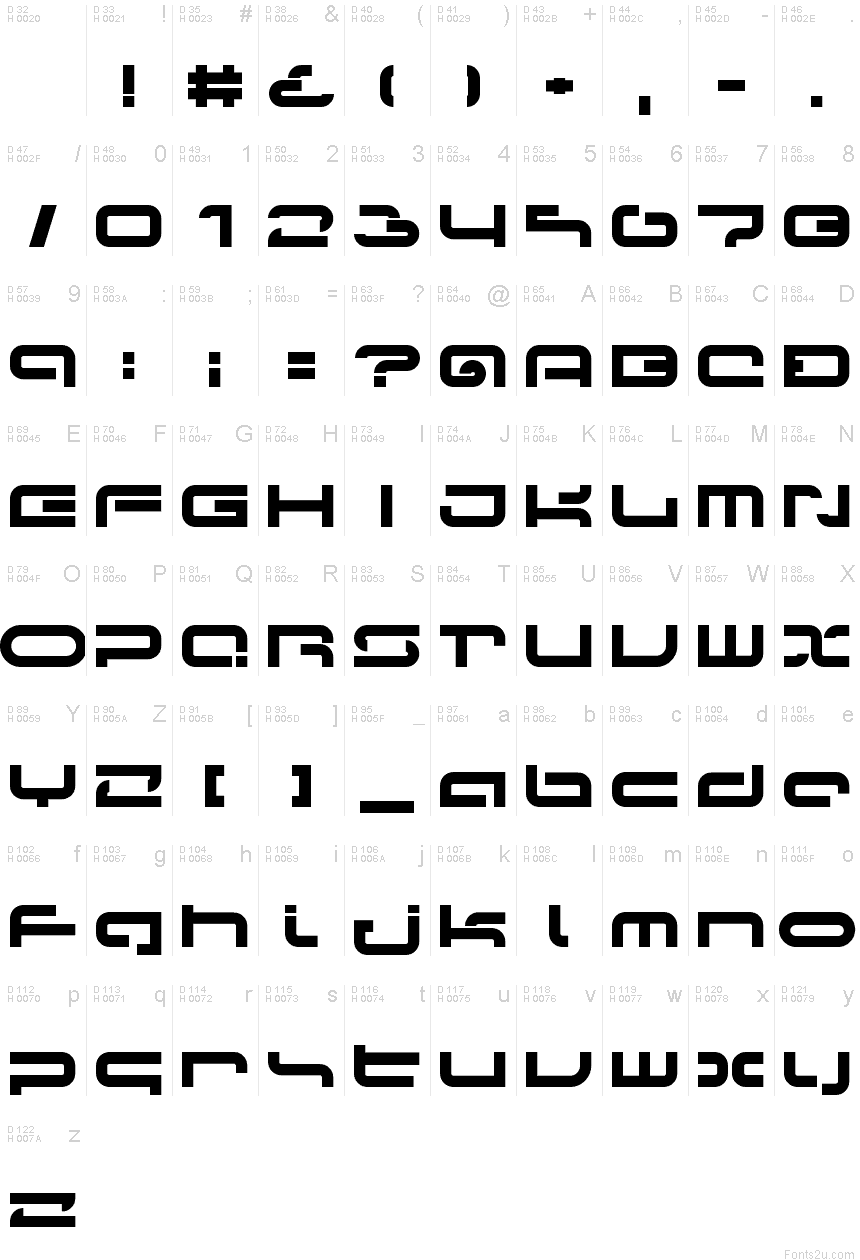
LVDC Papicon Font
LVDC Papicon di Lovedesign co. è un font display futuristico e gratuito, caratterizzato da forme rettangolari arrotondate, angoli aperti e tagli decisi che conferiscono a ogni carattere un ritmo segmentato e meccanico. La struttura segue una costante logica quadrata, in cui le curve morbide sono smussate da interruzioni rette e spazi interni compatti che mantengono il design coerente.
LVDC Papicon è un font gratuito perfetto per loghi tecnologici, titoli di poster, UI di giochi, motion graphic e segnaletica di eventi dove si richiede uno stile geometrico e nitido. Le sue curve massicce e le forme divise donano alle applicazioni un tocco digitale deciso, senza bisogno di ulteriori decorazioni.